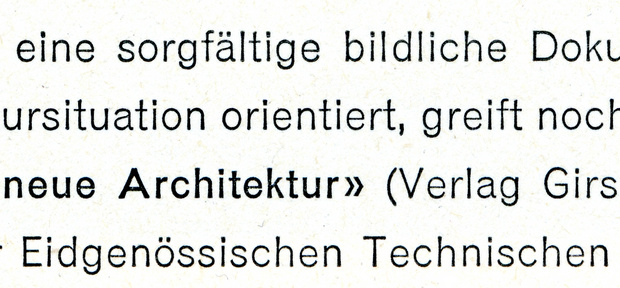
Schriftart im Du
Weiss jemand wass das für eine Schrift ist, und ob sie digital erhältlich ist?
Eine änliche wäre auch interessant. Sie erschien in der Zeitschirft «Du» im November 1960.
Deine Vorlage ist leider sehr grob aufgelöst.
Aber soviel ich erkennen kann, dürfte es sich um die „Grotesque“ handeln.
Diese Schrift gab es damals im Bleisatz und gibt es auch heute noch digital unter dem selben Namen.
Da Du auch nach ähnlichen gefragt hast: Als Vorlage für die Monotype-Grotesque kann die Venus gelten. Die mir bekannten Digitalisierungen haben aber alle irgendwelche Mängel. Bei der von URW beispielsweise wurde offenbar in den aufrechten Schnitten das Eszett geändert.
Die Venus kommt sehr nahe, leider ist die etwas liebloss digitalisiert.